無償フォント(RequaxFonts VlarkFonts ZerivsFonts)
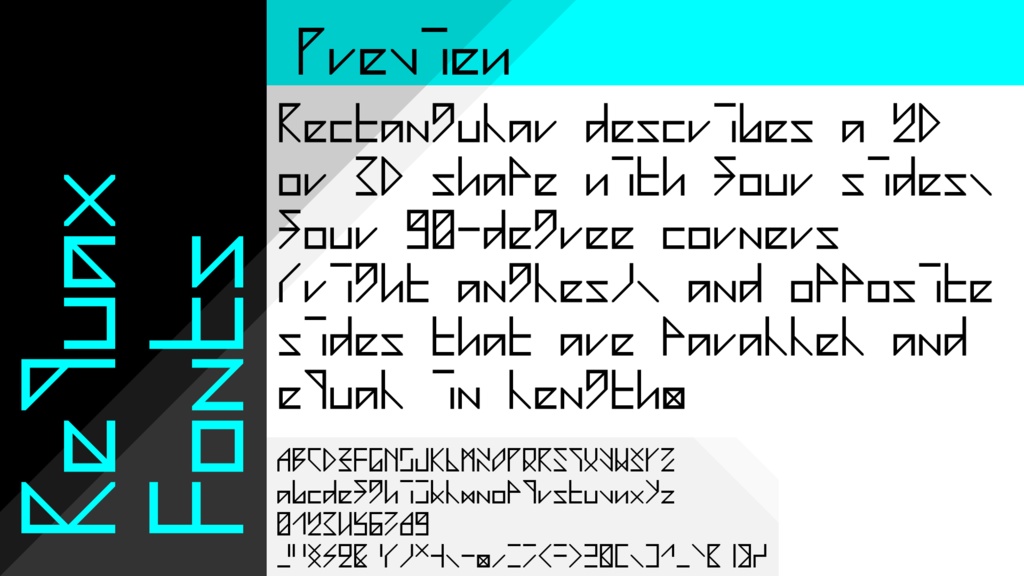
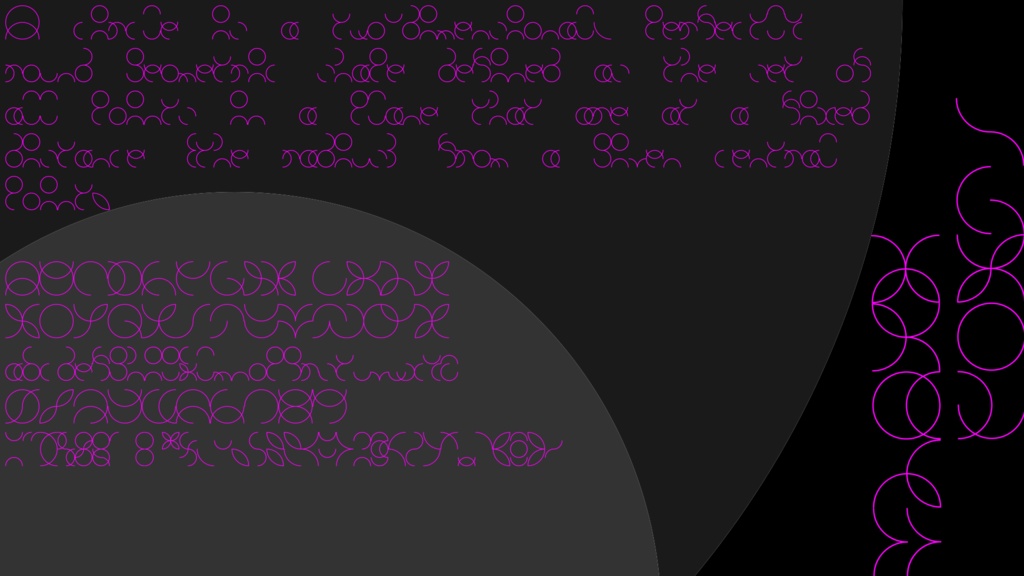
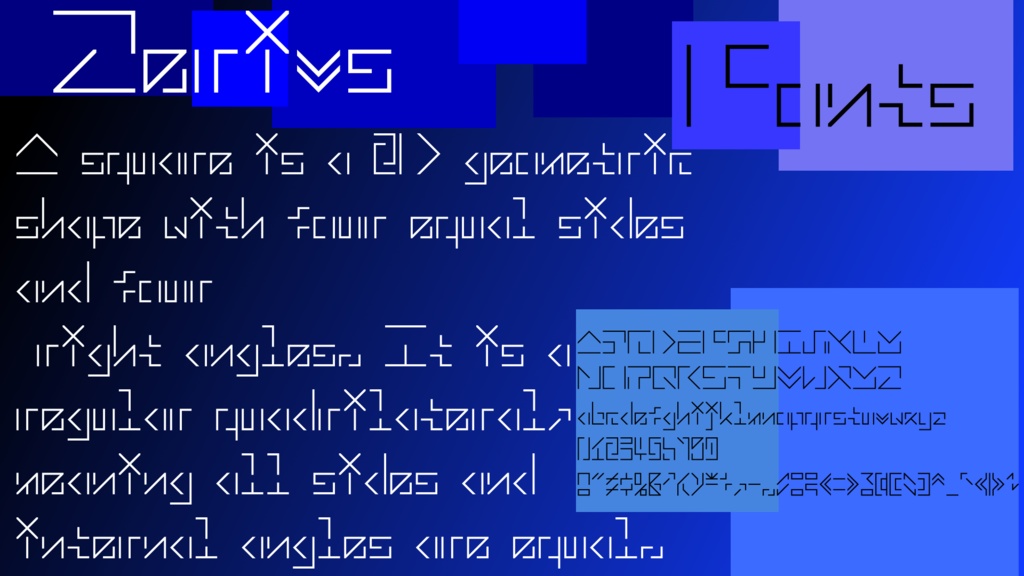
フォントの内容は以下の通りです 1.Requax Fonts (直線主体の近未来的な幾何学的フォント 可読性は比較的高め) 2.Vlark Fonts (円と弧のみから制作した異世界的なフォント 可読性は最も低い) 3.Zerivs Fonts (直線主体、主に文字が分断されたフォント 可読性は中間程) ロゴやデザインなどご自由に使用してください。 基本いかなる場面にも使用しても構いませんが、使用する際は以下の点に気を付けてください。 1.自作発言をしないこと 2.イメージを非常に大きく損なうような使い方をしないこと 3.作者や他の人に迷惑を掛けない使い方をすること 制作日:2025年12月05日 作者:すらがめ(X:Suragame_C_1A)